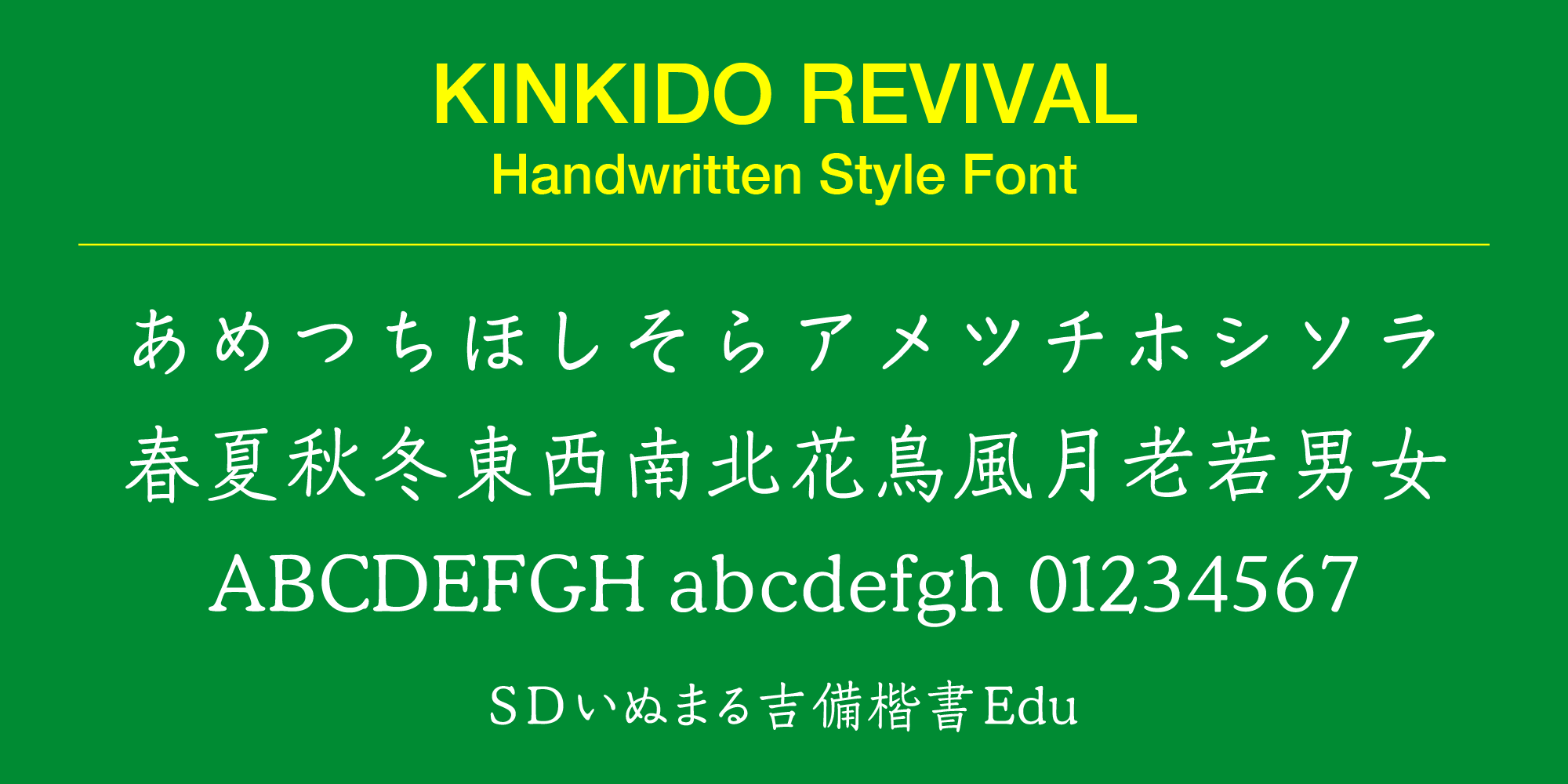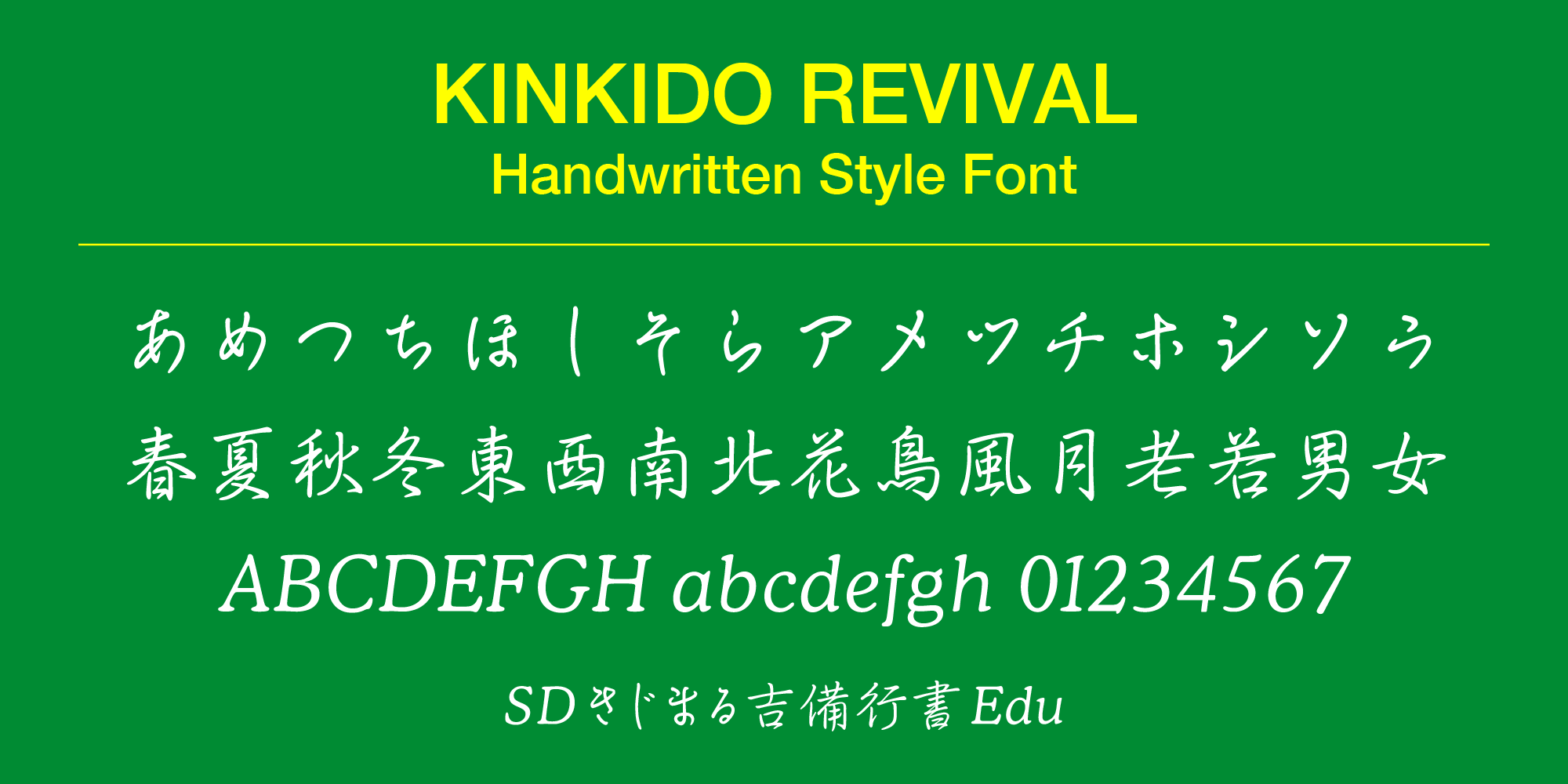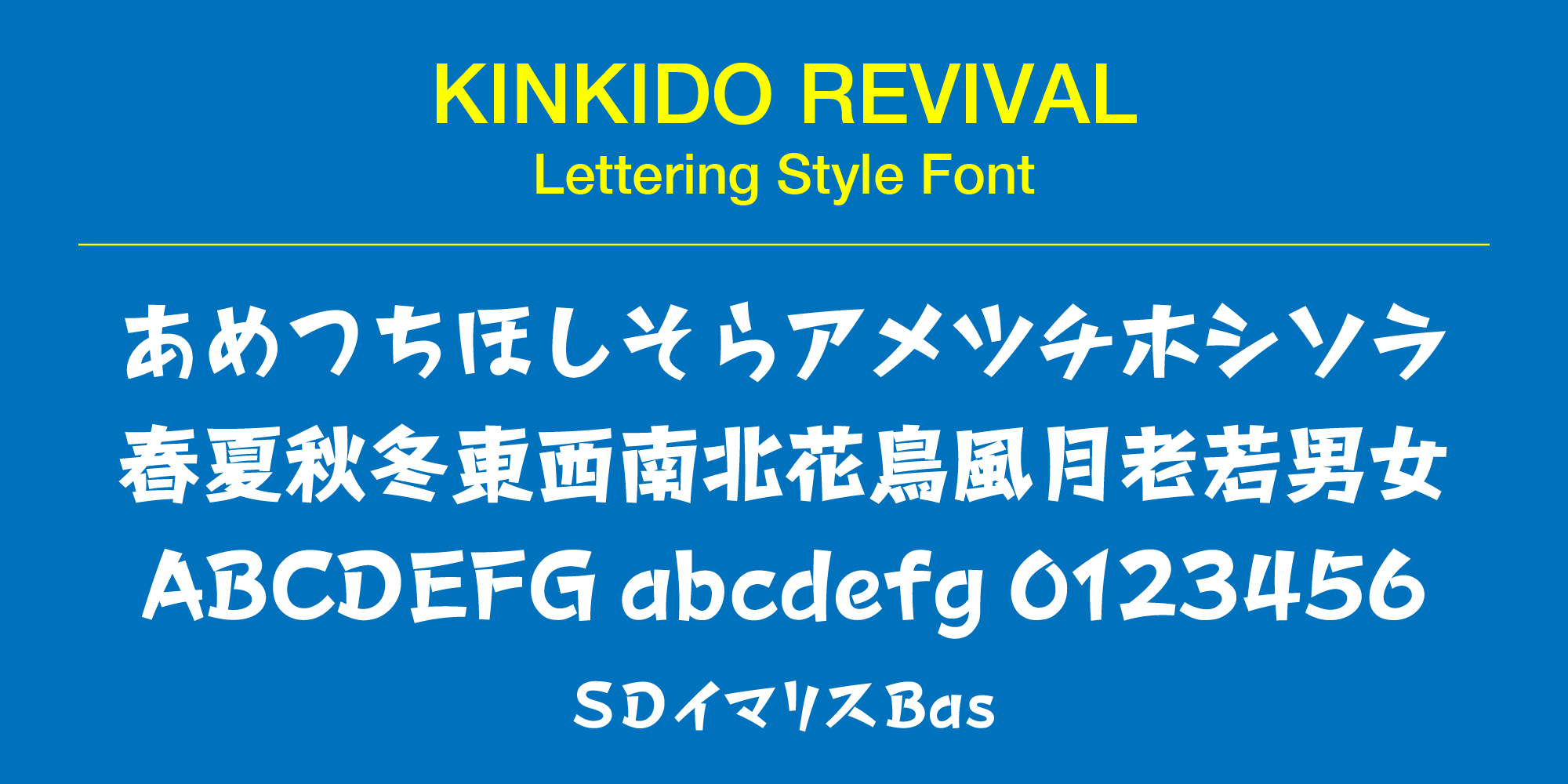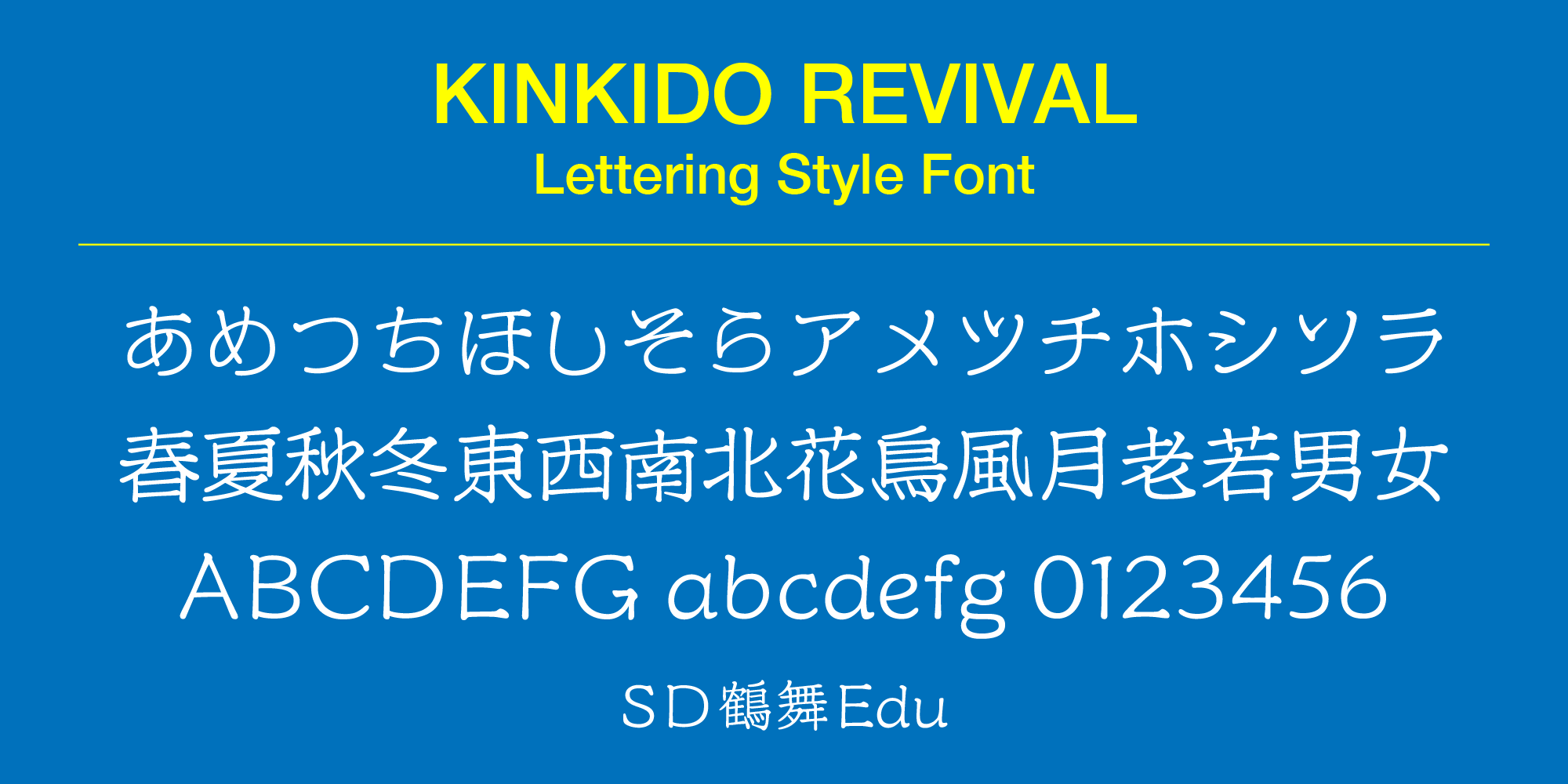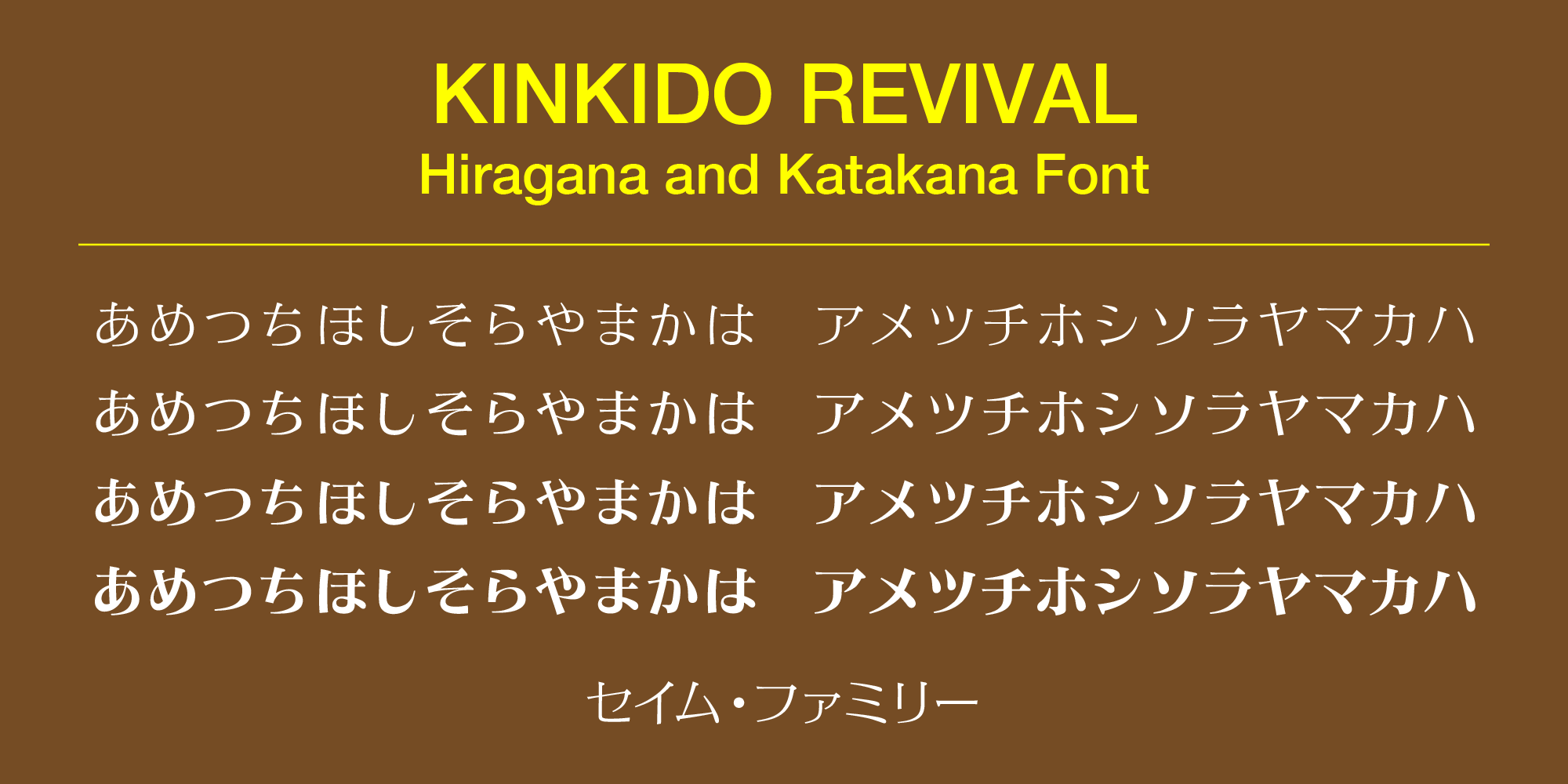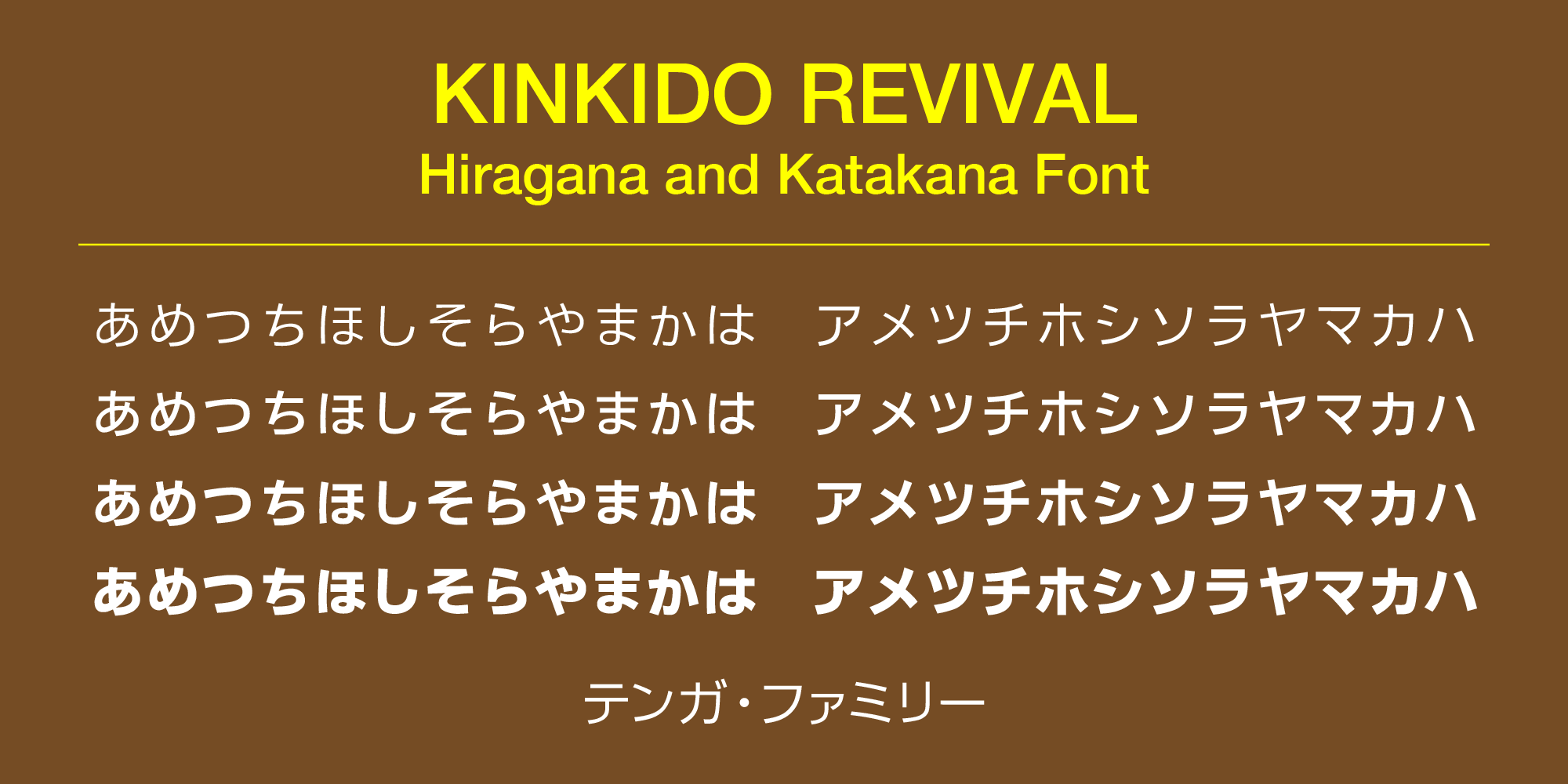
フォントサービス「Monotype Fonts」「MyFonts」「FONTPLUS」に欣喜堂の17書体を追加
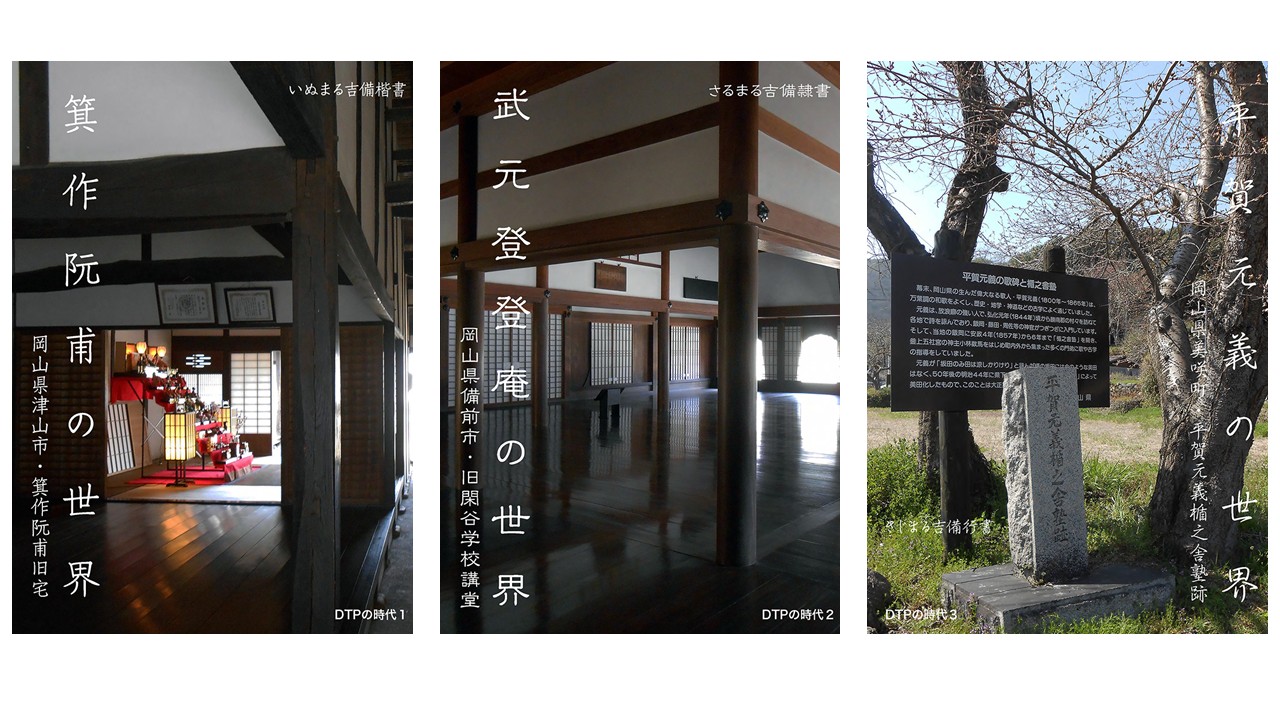
| 【欣喜堂のご紹介】 欣喜堂は、有限会社今田欣一デザイン室が手掛けるファウンダリーになります。今回、「欣喜堂リバイバル」(KINKIDO REVIVAL)として、1997年から2000年までに制作したカスタムメイド書体の復活プロジェクトです。手書きフォント(Handwritten Style Fonts)は書写の基本である楷書体、行書体、隷書体をベースに、デザインフォント(Lettering Style Fonts)は近世の江戸文字風、近代の図案文字風、現代の企業制定文字風をベースにしています。 |
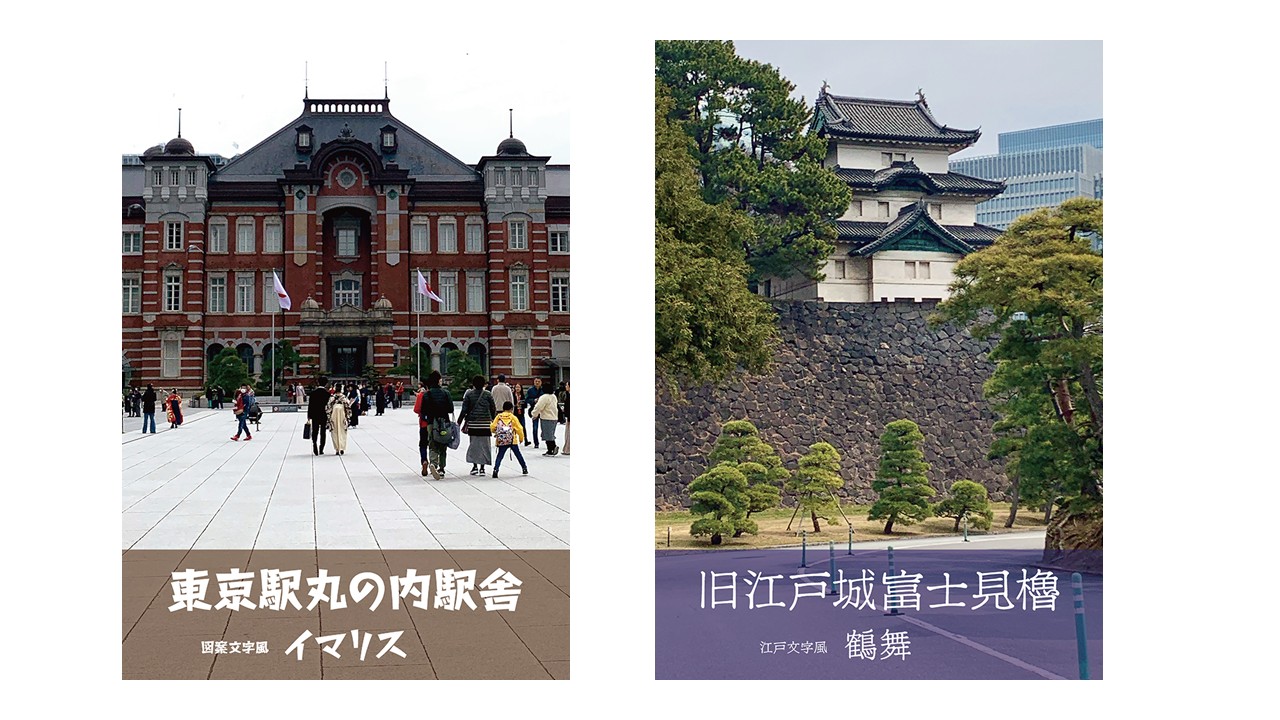
【提供書体一覧】
| いぬまる吉備楷書 手書き風の「楷書体」です。本文向けの書体で、小学校で習う1026字の漢字が使用できます。 |
| きじまる吉備行書 手書きの「行書体」です。本文向けの書体で、小学校で習う1026字の漢字が使用できます。 |
| イマリス 装飾的・図案的な要素としてデザインした図案文字をベースにした書体です。見出し向けの書体で、JIS第一水準漢字の2965字が使用できます。 |
| 鶴舞 江戸文字をベースにした書体です。見出し向けの書体で、JIS第一水準漢字の2965字が使用できます。 |
| ウダイ 現代的なアンチック体の和字書体です。見出し向けの書体で、4ウェイトをご用意しています。(W3 / W5 / W7 / W9) |
| セイム 明朝体(漢字)と組み合わせる現代的な和字書体です。見出し・本文に最適で、4ウェイトをご用意しております。(W3 / W5 / W7 / W9) |
| テンガ ゴシック体(漢字)と組み合わせる現代的な和字書体です。見出し・本文に最適で、4ウェイトをご用意しております。(W3 / W5 / W7 / W9) |